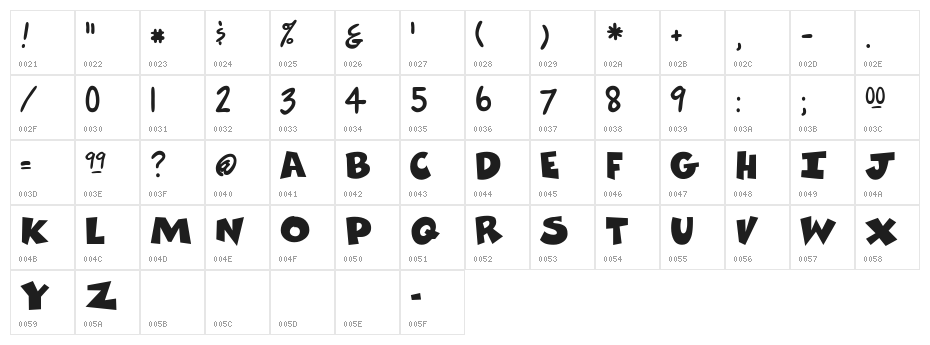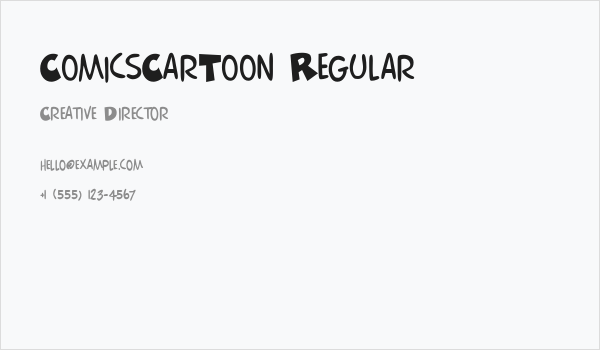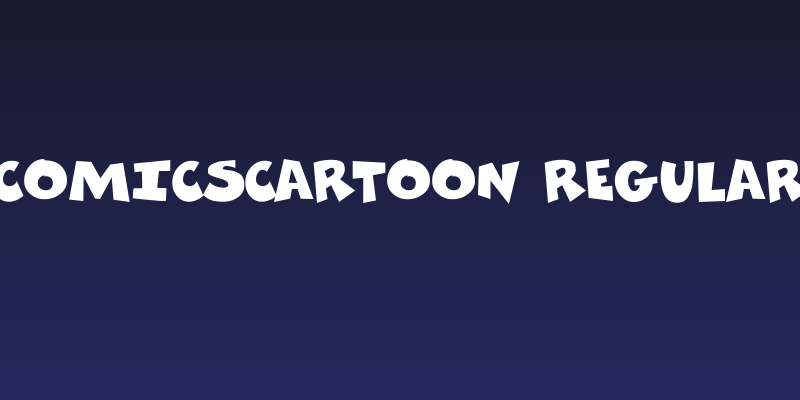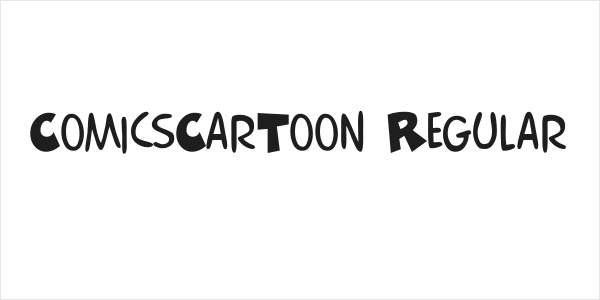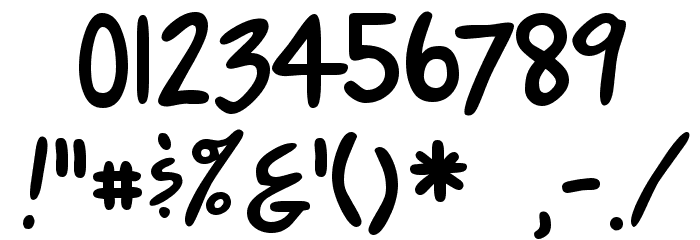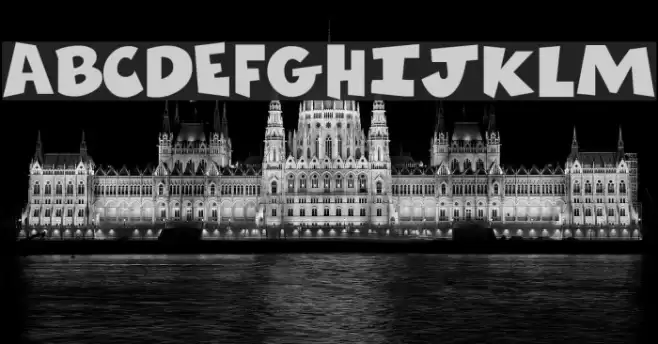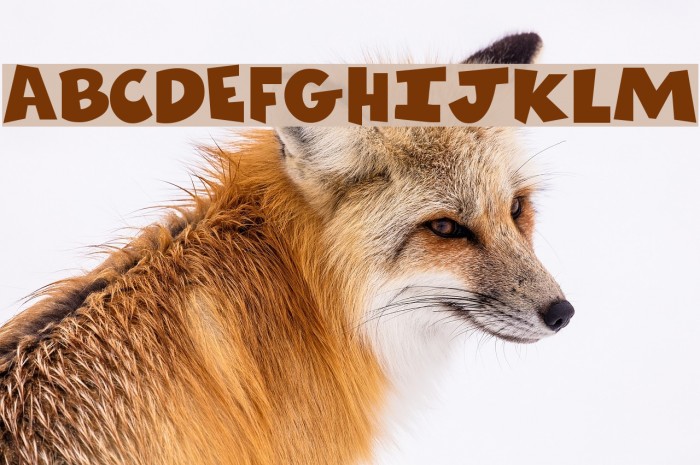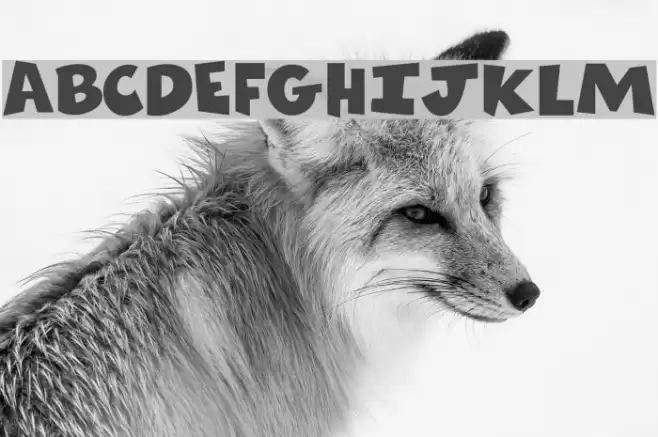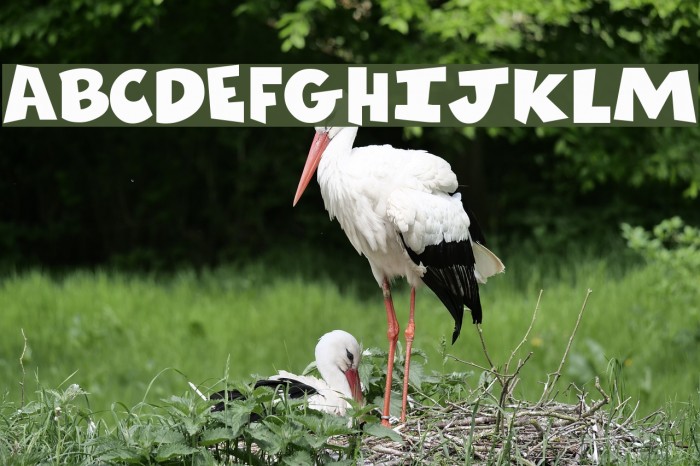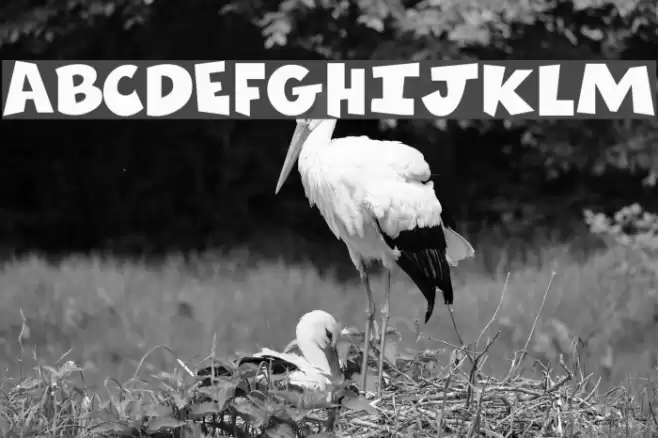
ComicsCarToon Regular Font
| Название | ComicsCarToon Regular |
| Категория | Cartoon |
| Общий стиль | Playful, Cartoonish |
| Рекомендуемые проекты | Ideal for children's books, comic strips, playful branding, and casual invitations. |